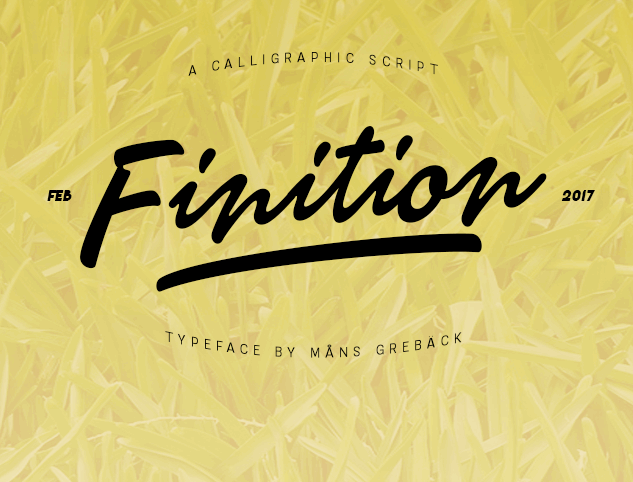
A fonte ‘Finition Font’, criada pelo designer sueco Måns Grebäck, oferece um tom suave e elegante, ideal para qualquer projeto que valorize a mão escrita. Seu estilo é perfeitamente adaptado aos aplicativos que buscam uma aparência natural e envolvente, sem perder a qualidade e o encanto de uma fonte real ou gravada. Com características levemente fluidas e linhas suaves, ‘Finition Font’ não apenas oferece um visual agradável, mas também oferece flexibilidade para diferentes usos. Seja em design gráfico, artes digitais, arte editorial ou criação de logotipos – esta fonte irá deixar seu trabalho com uma sensação de naturalidade e autenticidade. Para aqueles interessados em adquirir um licenciamento comercial, os detalhes estão disponíveis no endereço: http://mn.sg/finition. Com certeza, a ‘Finition Font’ se destaca como uma escolha inteligente para qualquer projeto que valoriza o equilíbrio entre estilo e facilidade de uso.